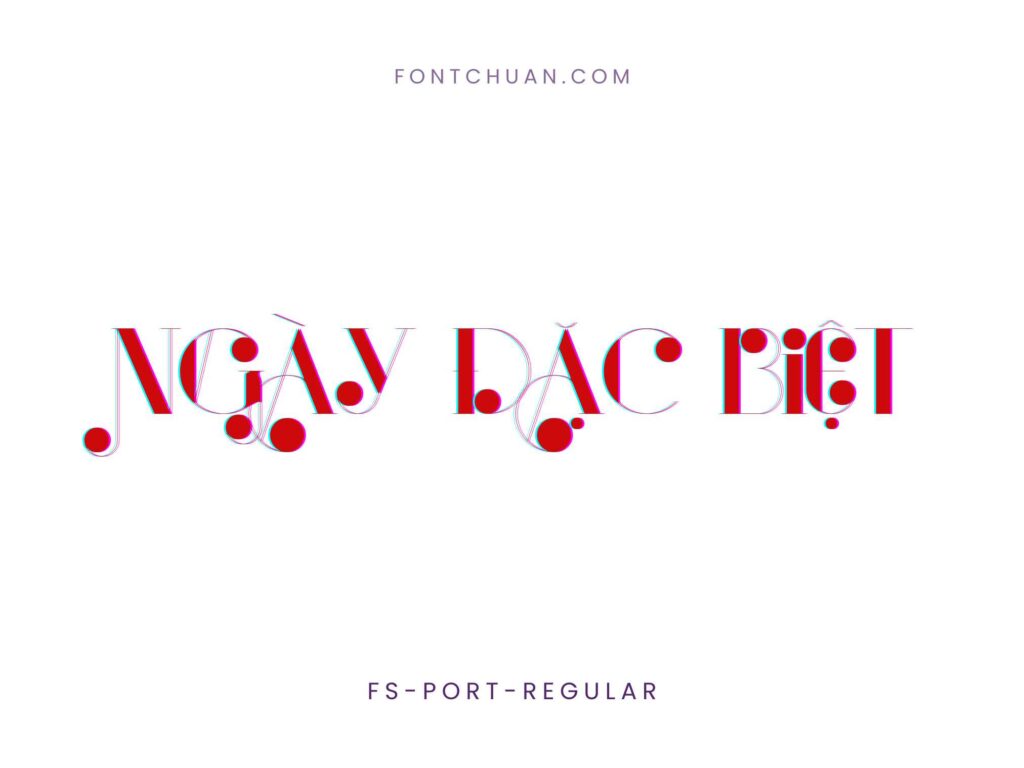
Font FS Fs Port Regular Việt Hóa
Tác giả Font: João Oliveira
Port là một kiểu chữ Didone thử nghiệm với phong cách hiện đại, được lấy cảm hứng từ các tác phẩm kinh điển của các bậc thầy như Bodoni và Didot, kết hợp với sự tinh tế của các kiểu chữ viết tay. Được thiết kế bởi João Oliveira và phát hành vào năm 2013, Port mang đến sự kết hợp độc đáo giữa các đường nét thẳng và tương phản mạnh mẽ của kiểu chữ Didone với sự uyển chuyển của thư pháp, tạo nên những ký tự sống động với các nét cong hình học có thể kết hợp theo nhiều cách khác nhau. Nhờ sự Việt hóa của Phông Chữ Việt, Port hỗ trợ đầy đủ các ký tự tiếng Việt, giúp người dùng dễ dàng áp dụng trong các thiết kế đa ngôn ngữ. Thành viên của Font Chuẩn đã sưu tầm và chia sẻ font chữ này nhằm đáp ứng nhu cầu của cộng đồng thiết kế.
Về đặc điểm thiết kế, Port bao gồm nhiều kiểu chữ với các biến thể như Port Regular, Port Regular Decorated, Port Medium và Port Medium Decorated, cùng với các bộ trang trí như Port Ornaments và Port Words. Mỗi ký tự đều có phiên bản mỏng, cung cấp sự linh hoạt cho các nhu cầu sáng tạo khác nhau. Font này đặc biệt phù hợp cho các dự án thiết kế như thương hiệu, thiết kế biên tập, giao diện người dùng và các ấn phẩm quảng cáo, mang lại sự chuyên nghiệp và tinh tế cho thiết kế. Ngoài ra, Port cũng phù hợp cho các sự kiện như lễ hội, sinh nhật, Valentine và Trung thu, tạo không khí ấm áp và gần gũi. Trong lĩnh vực ngành nghề, Port được ứng dụng rộng rãi trong quảng cáo, thiết kế thiệp cưới, giáo dục và công nghệ, góp phần tạo nên sự độc đáo và thu hút cho các sản phẩm và thương hiệu.